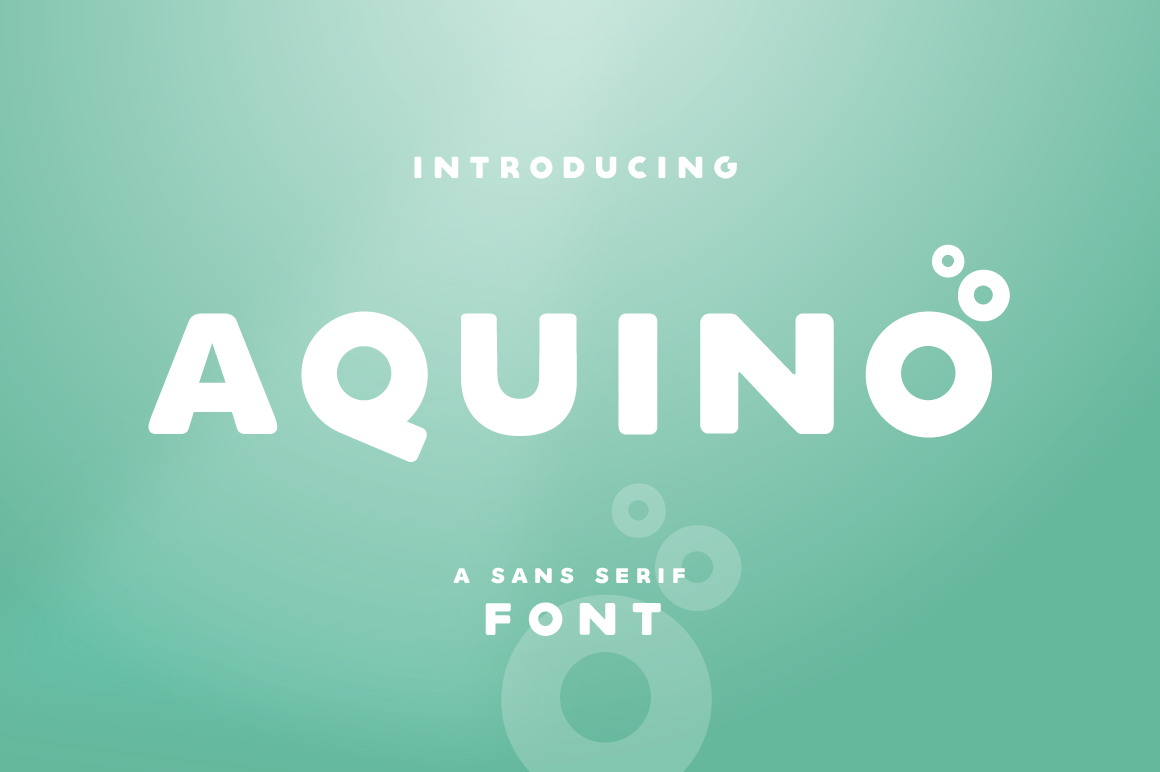
A ‘Aquino Font’ é uma elegante tipografia sans-serif que surge com a destreza do designer Hamilton. Esta fonte de estilo limpo e agressivo é perfeita para novos projetos, garantindo um visual contemporâneo e fresco. Ideal tanto para textos grandes quanto para legenda e subtítulos, ela traz uma sensação moderna às criações digitais, criando um impacto imediato e atraente. Perfeito para designers que buscam incorporar um toque de simplicidade no design de gráficos digitais, a ‘Aquino Font’ é uma escolha estratégica para qualquer projeto visual atualizado.